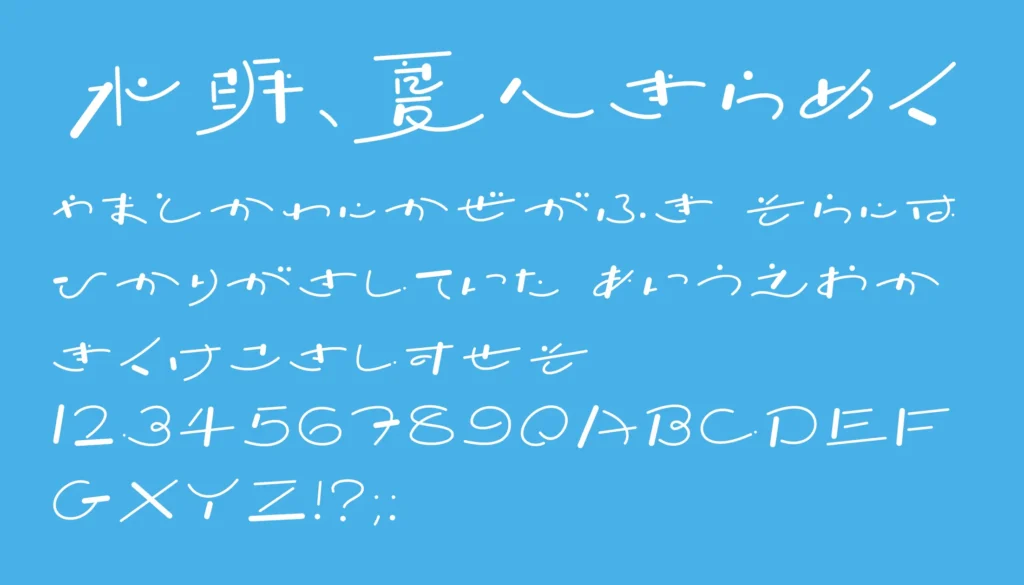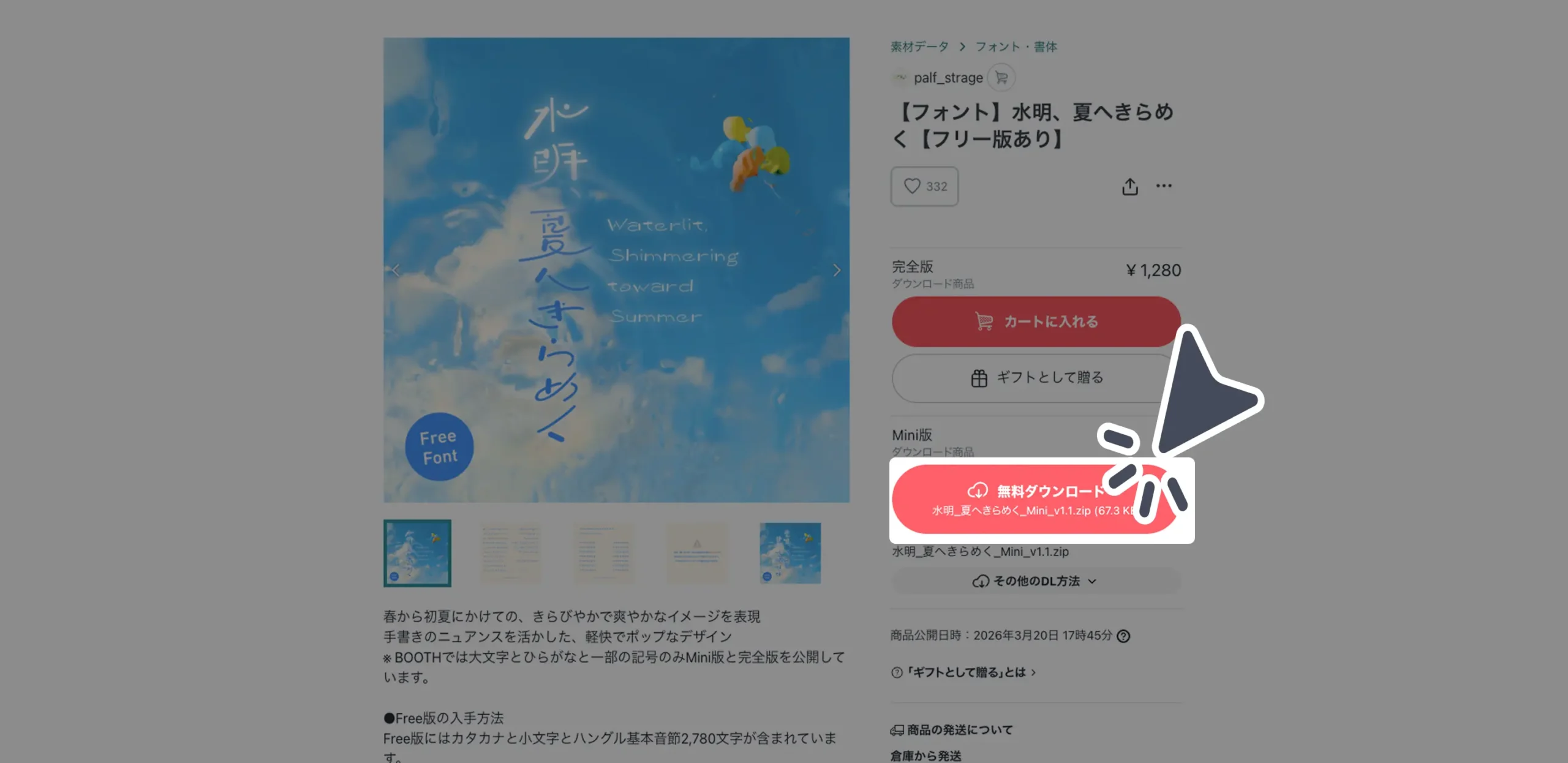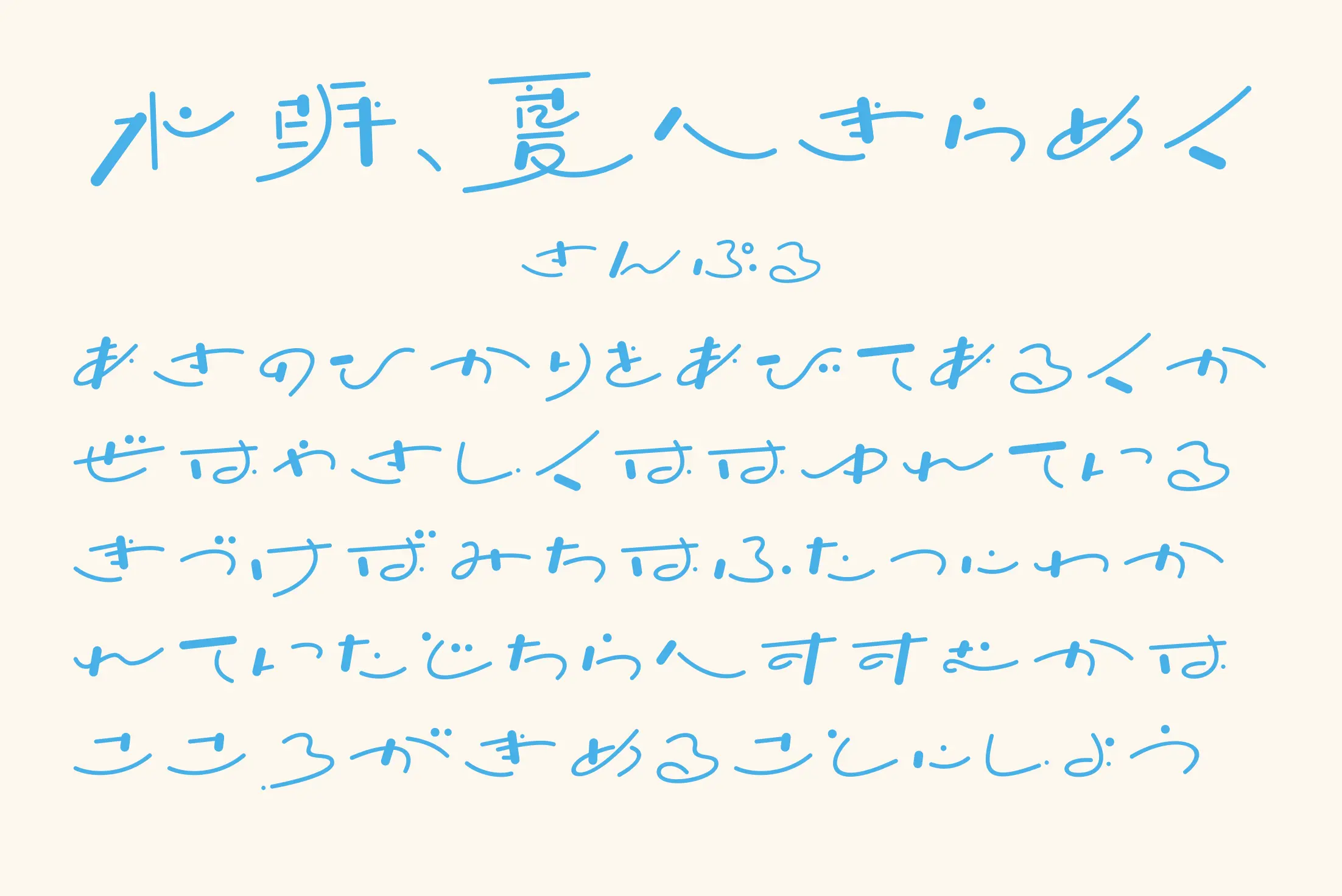
涼しげな手書き感と、水面に反射する光みたいな“ゆらぎ”が魅力のデザイン書体です。細めの線で構成されているので圧迫感がなく、夏の青春感・透明感・やさしい空気感を自然に演出できます。特にMV風タイトル、詩的なロゴ、エモ系の動画テロップ、ZINEや同人表紙との相性がかなり良いタイプ。ひらがなの丸みが柔らかく、読むというより“雰囲気で浸る”フォントって感じの存在感があります。
水明、夏へきらめく